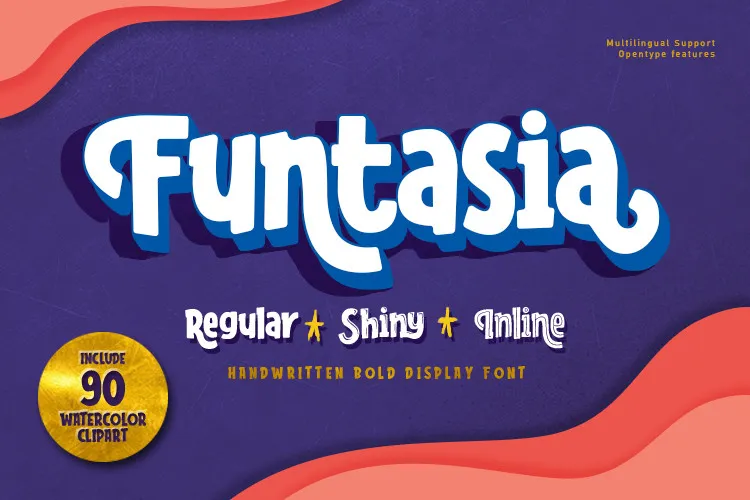
A Funtasia Display Font é uma fonte bold-Fun com letras limpas que parece simples e moderna. Este estilo único traz um toque de brincadeira e, às vezes, até mesmo uma sensação infantil para qualquer projeto gráfico. Ideal para crianças, jogos de móveis, aplicações dos títulos, cartas de cumprimento engraçadas, embalagens de refeições, logotipos e muito mais, onde o uso de desenhos animados ou grafismo abstrato simples é preferido. Com três estilos diferentes, a Funtasia Display Font é perfeitamente adaptável para muitas aplicações em designs contemporâneos que valorizam uma dose extra de criatividade e diversão. Experimente-a no seu próximo projeto e faça sua marca soar mais divertida e vibrante.
Designer: RVST